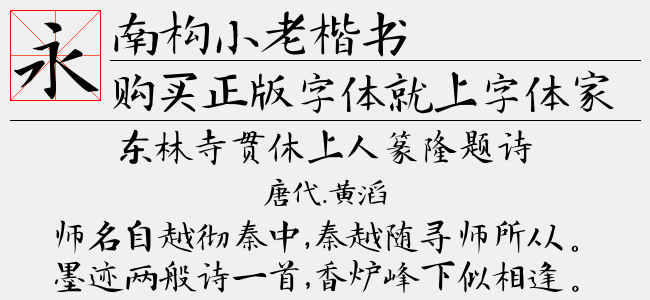
南构小老楷书
字体作者:朱学文
字体名称:南构小老楷书
字体家族:南构系列
书体类型:手写体
来源类型:官方发行
字体公司:南构字库
字体设计:南构签约设计师
作者职业:设计师
南构小老楷书
这款南构小老楷书字体是一款毛笔书法楷书字体,笔画遒劲,结体严谨,字形特点突出,良好流畅的笔画表现,使这款字体很有视觉冲击力,在许多场景中使用都非常的不错,如广告招牌,背景海报,标题大字等。